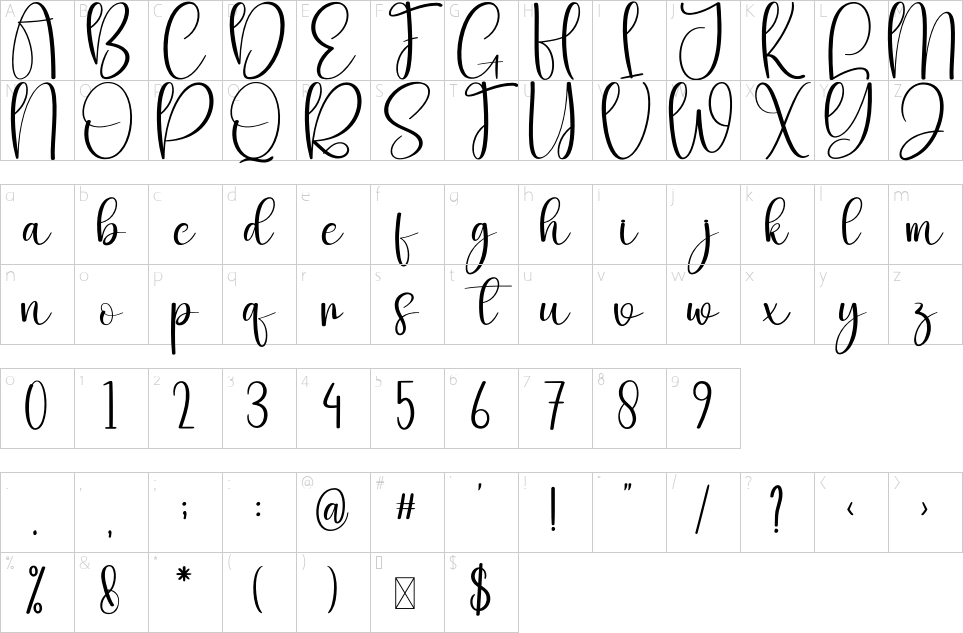
Delight Birthday Font – Download Grátis
Descubra Delight Birthday Font, uma agradável e encantadora fonte para celebrar aniversários. Esta elegante fonte foi criada por scratchones e já foi baixada 116 vezes. Perfeita para adicionar um toque especial aos doces aniversariantes ou qualquer outro documento de texto em seu computador, Delight Birthday oferece uma experiência visual agradável e divertida. Seja o aniversariante o encantado com seu nome brilhando na tela ou apenas tenha mais diversão ao criar documentos que combinem perfeitamente com datas especiais. Não deixe de baixar esta font adorável para enriquecer suas criações digitais e personalizá-las ainda mais, seja para aniversários festivos ou simplesmente para um dia especial em qualquer projeto.